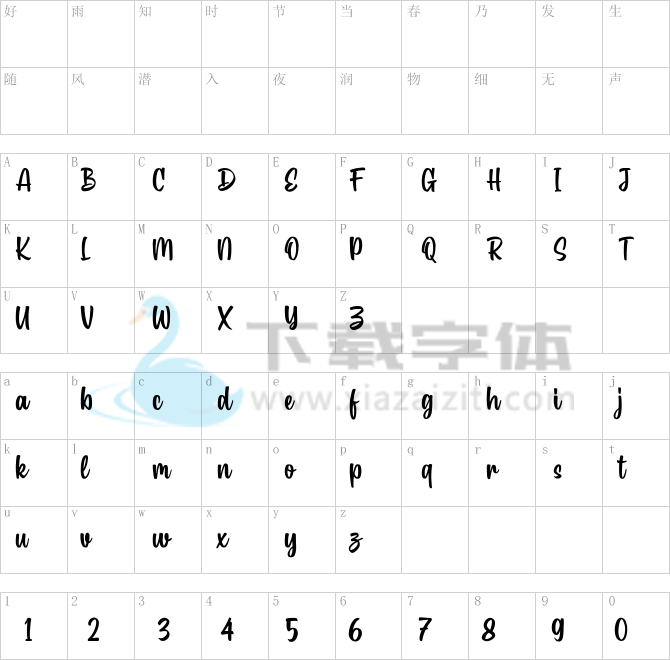
Andoly Cokie.ttf字体下载,这款字体结构工整、笔画清晰,兼顾美观与易读性,适用于标题、正文、海报、包装、LOGO 等多种场景。字形优雅稳定,风格百搭耐看,适配日常排版与创意设计,让文字呈现更舒适、更具质感。Andoly Cokie.ttf字体下载一笔一画,皆是细节,以均衡的比例、流畅的线条打造舒适视觉体验,字形端正大气,风格简约现代。无论是商业设计、品牌宣传还是日常排版,都能轻松驾驭,让文字更有格调与力量。Andoly Cokie.ttf字体下载字体下载。